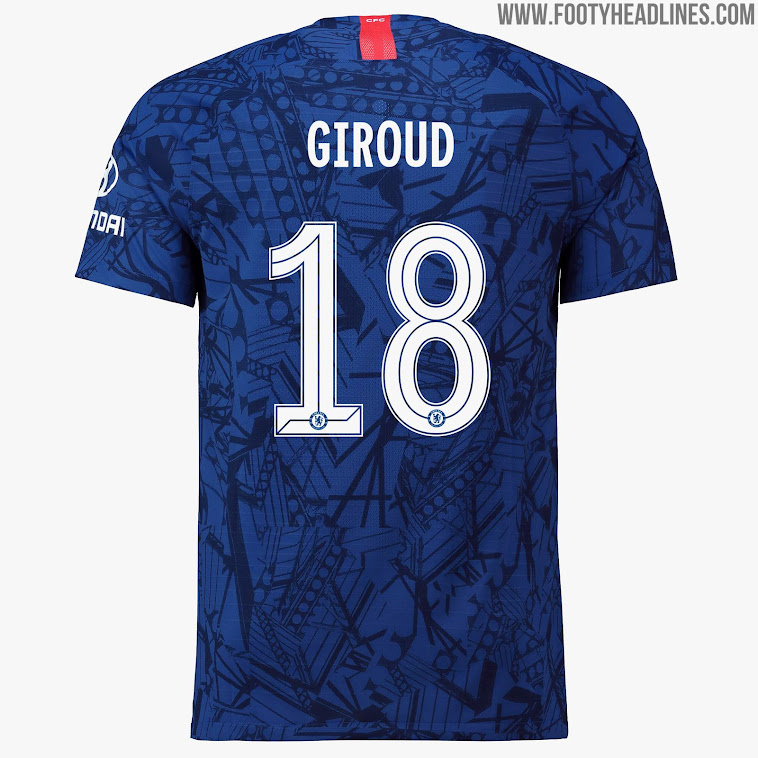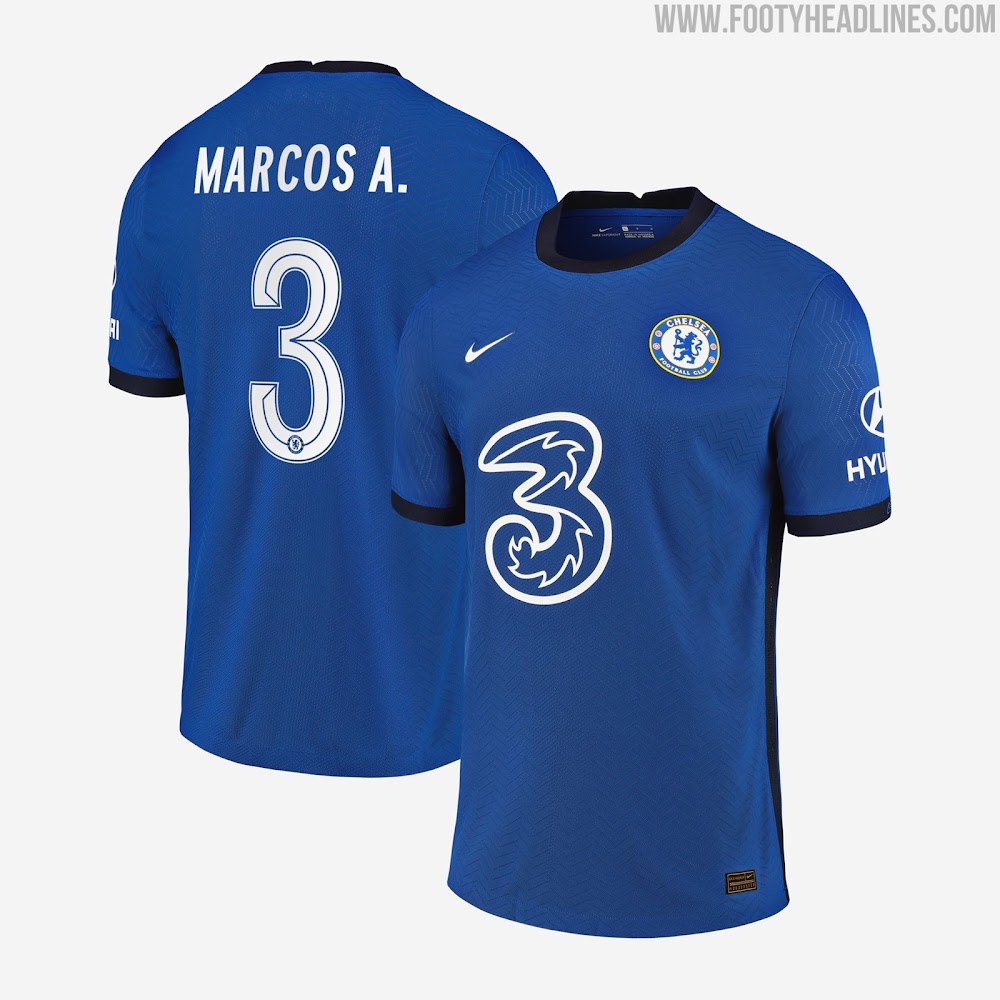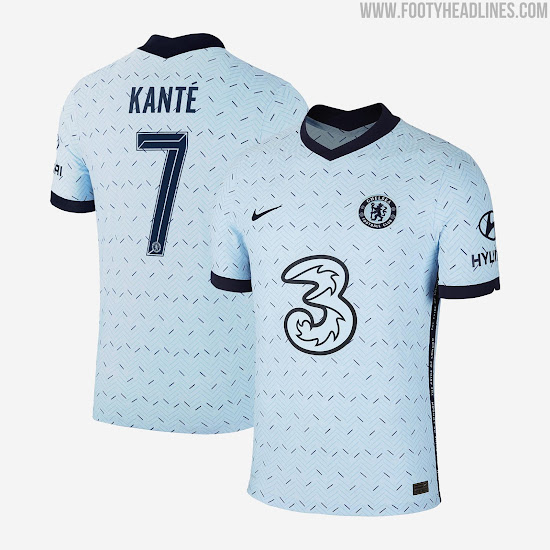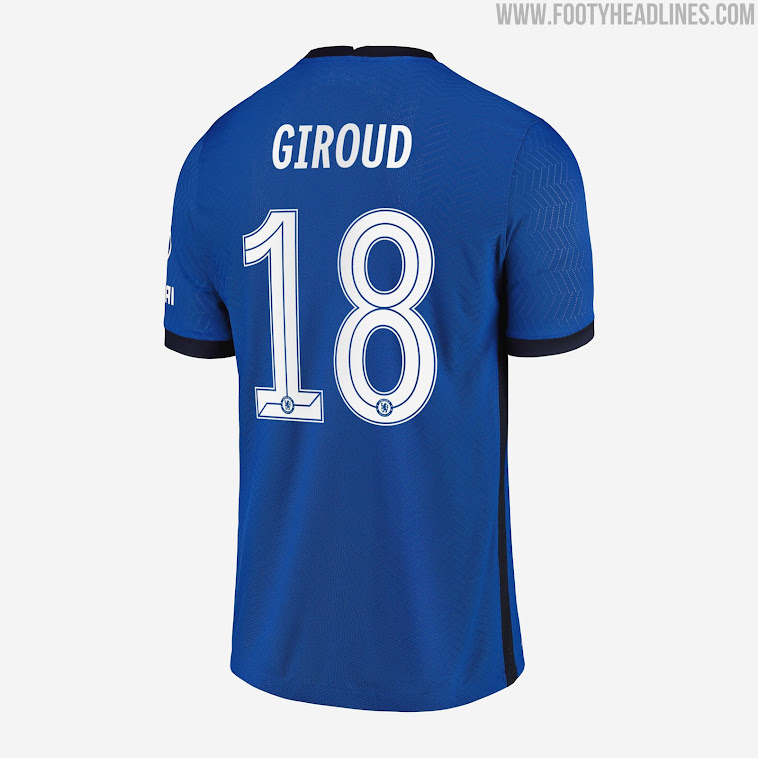
Chelsea wird "alte" Trikot-Schriftart für Saison 2020/21 behalten
Chelsea FC debütierte im Champions-League-Spiel gegen Bayern München die Pokalversion des 2020-21 Heimtrikots. Dabei erhielten wir auch einen Blick auf das Trikot mit der individuellen Pokal-Schriftart des Clubs.
Chelsea 2020-21 Pokal Trikot-Schriftart wird aus der vergangenen Saison übernommen
Die Chelsea 2020-2021 Trikot-Schriftart ist nicht neu, sondern dieselbe, die für die Saison 2020/21 eingeführt wurde. Die benutzerdefinierte Trikot-Schriftart 2019-20xx von Chelsea hat einen stilvollen Look mit dünnen Linien.
Wir sind der Meinung, dass die "alte" Chelsea Trikot-Schriftart sogar noch besser zum Trikot passt als zum 2019-20 Heimtrikot.